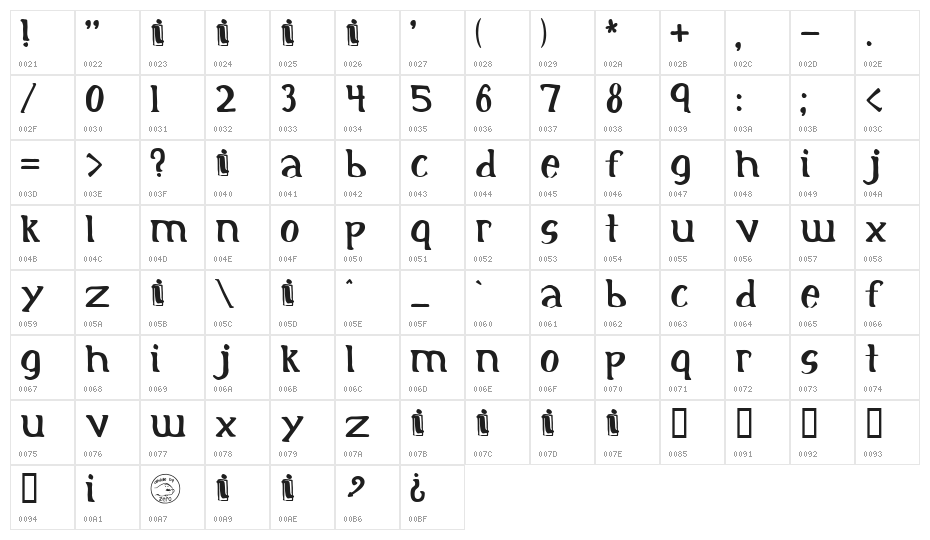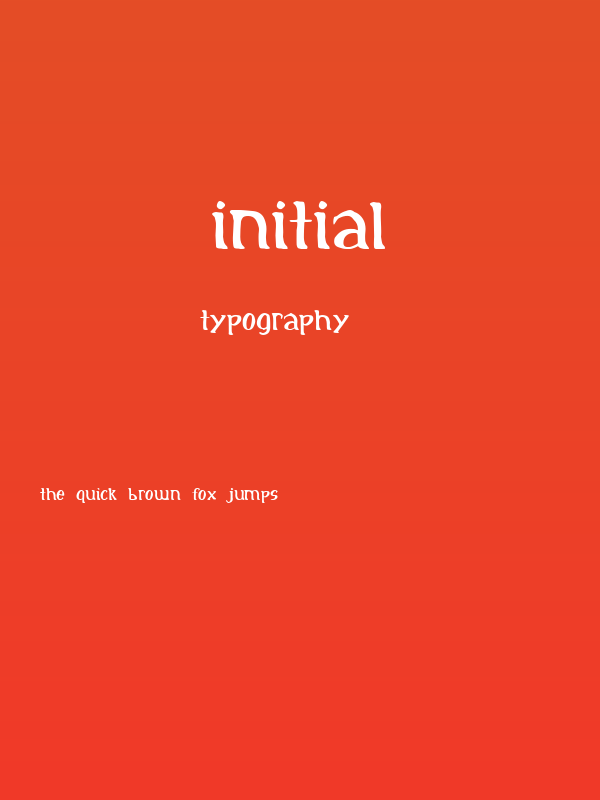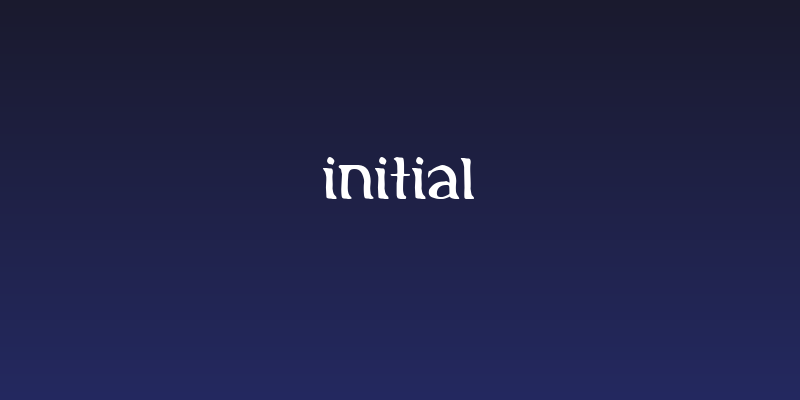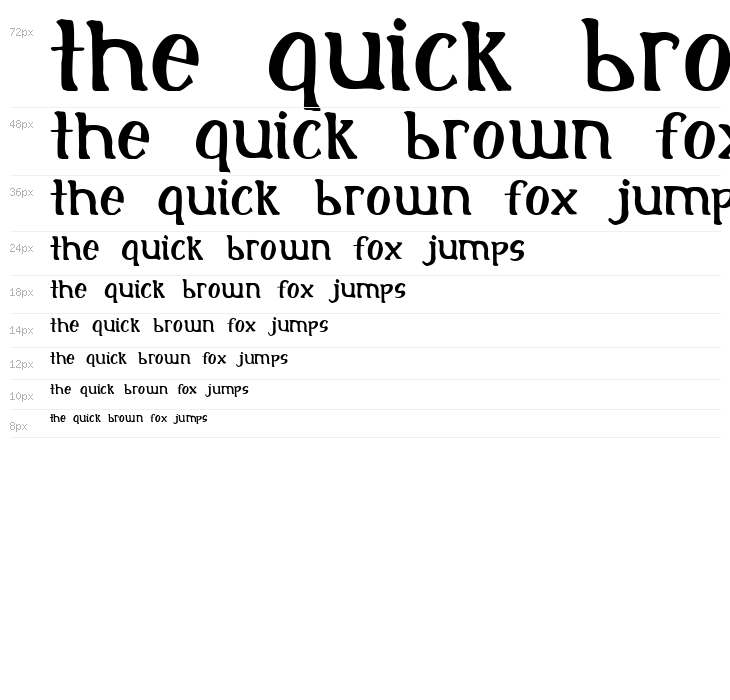
Initial Font
| Gesamtstil | Whimsical, Playful |
| Vorgeschlagene Projekte | Great for children's books, playful branding, greeting cards, and creative posters. |